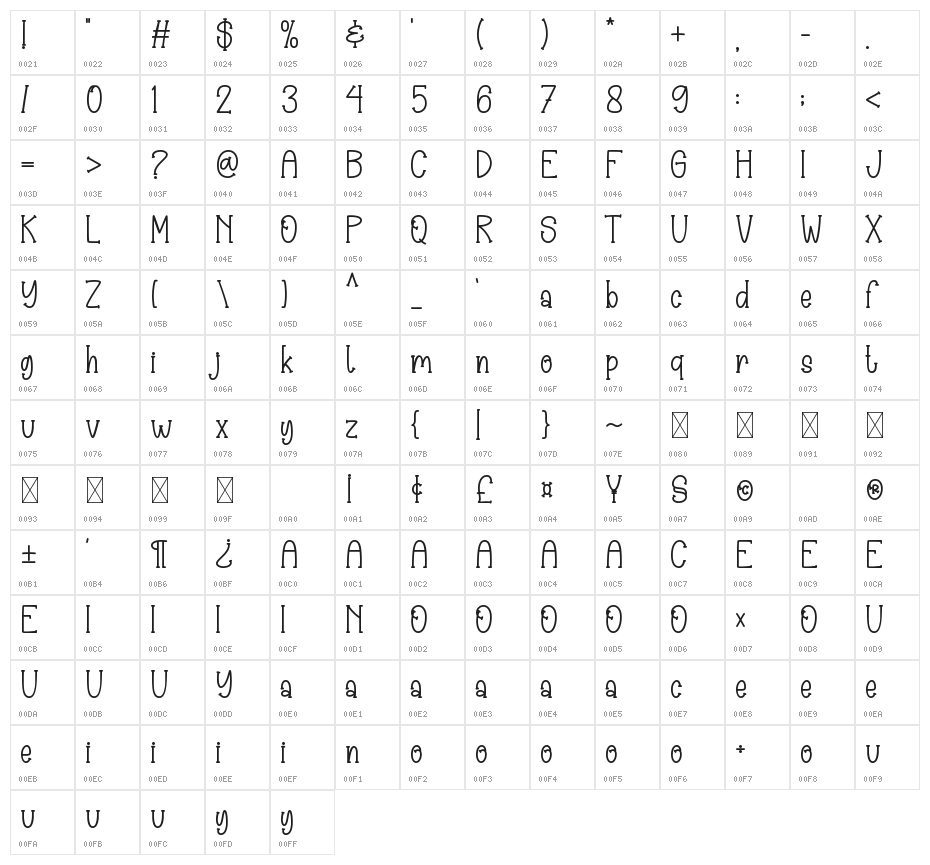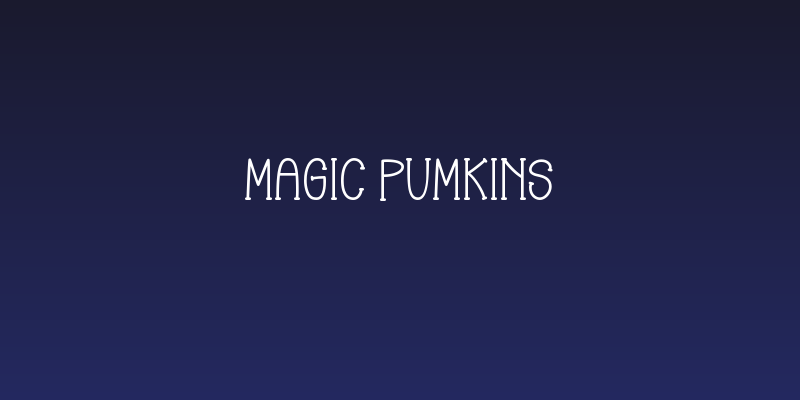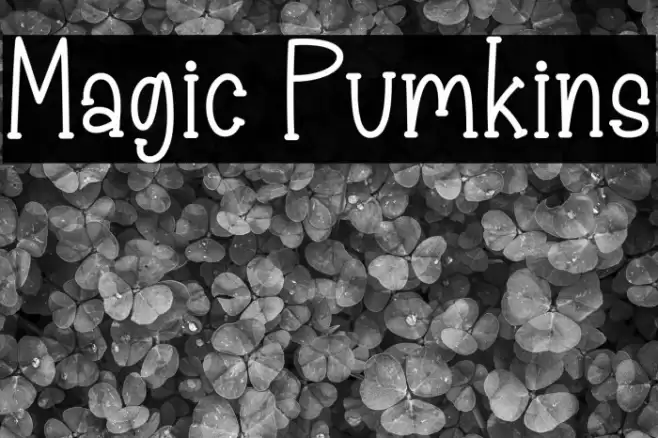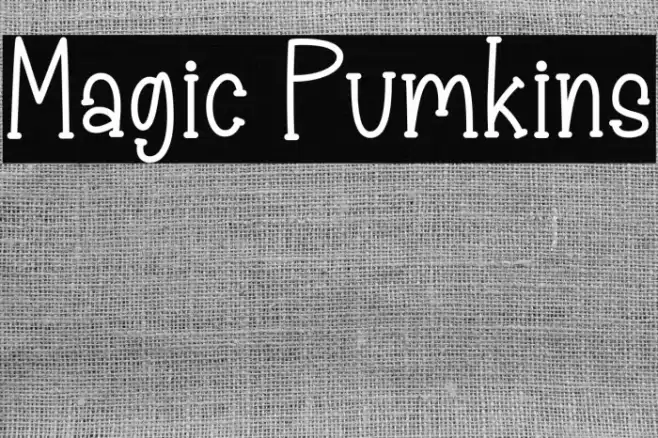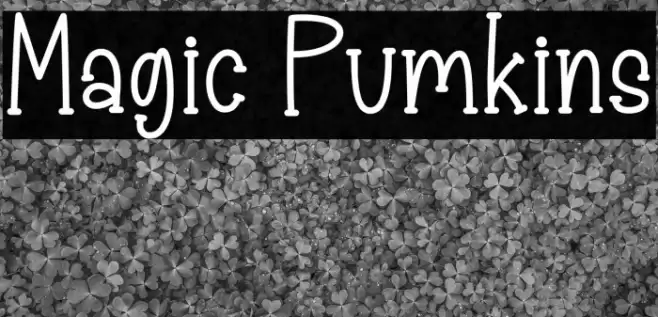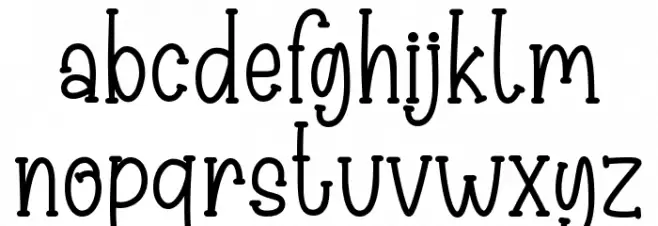
Magic Pumkins Font
| النمط العام | Playful, Whimsical |
| حالة الاستخدام | Headlines, Logos, Invitations |
| مشاريع مقترحة | Ideal for children's books, playful branding, festive invitations, and creative posters. |